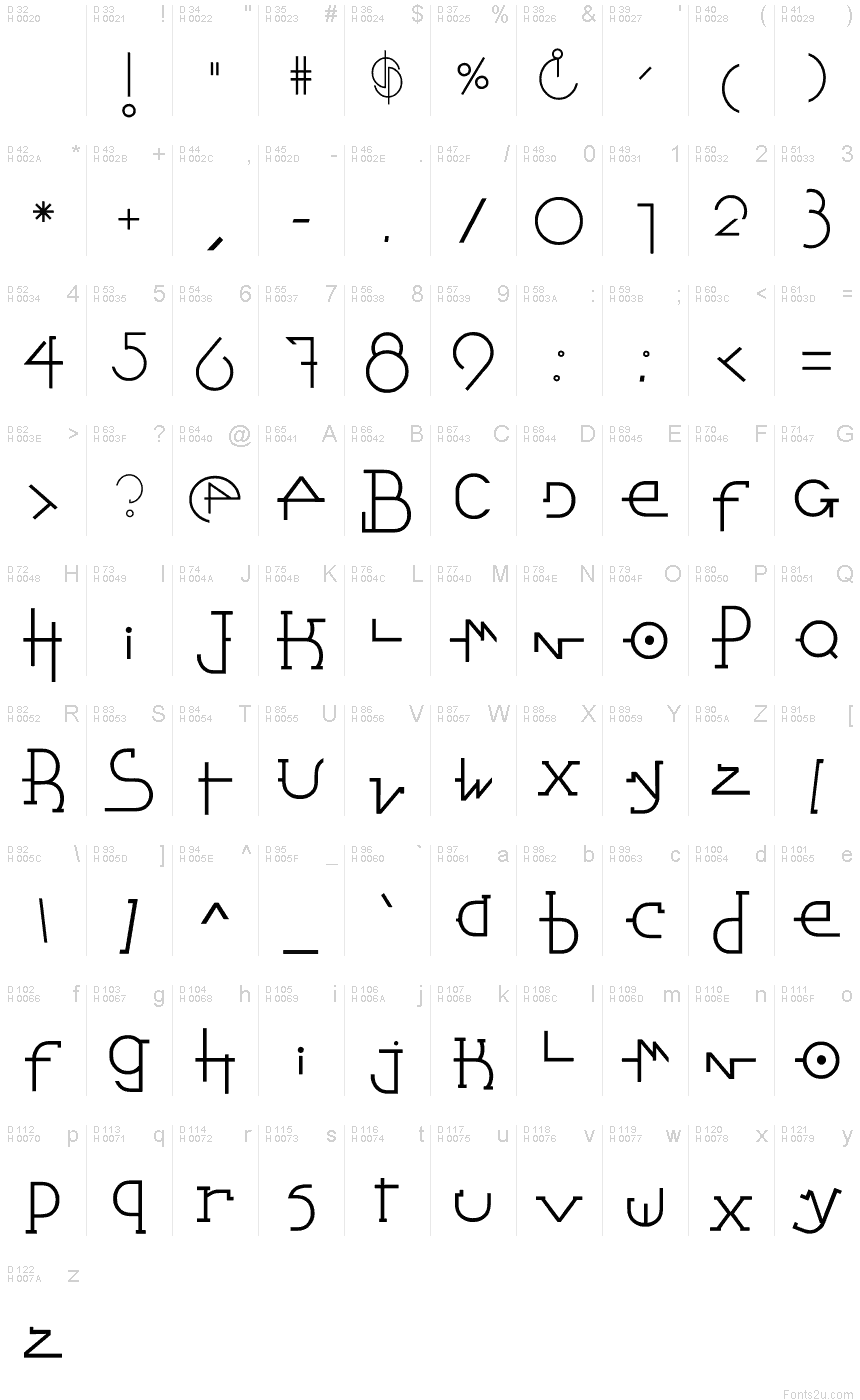
Stretched Signature Best Italic, navržený Galdinem Ottenem, je bezplatné geometrické display písmo s útlou, jednolinkovou konstrukcí. Dlouhé rovné tahy se setkávají s širokými křivkami a úsporné tvary písmen využívají otevřená napojení a prodloužené příčky pro vytvoření technické, neobvyklé siluety.
Jeho retrofuturistický charakter se hodí pro sci-fi plakáty a vizuály elektronické hudby. Tenká konstrukce se rovněž hodí pro módní branding a herní rozhraní s chladným, technickým vyzněním. Obvodové čáry, mřížky a minimální grafika rozhraní mohou zopakovat rovné tahy a oblé přechody písma jako součást okolního obrazu.
This font was conceived according my self signature that you can see in all my artwork in my blog as well street art writings, and the it can be used in diverses ways and artstylles, it can be used of the simplest the most sophisticated work until. Its more important characteristic is the flexibility of its connections, for being linked becomes infinitely flexible being able to transpose the limitations of any space.